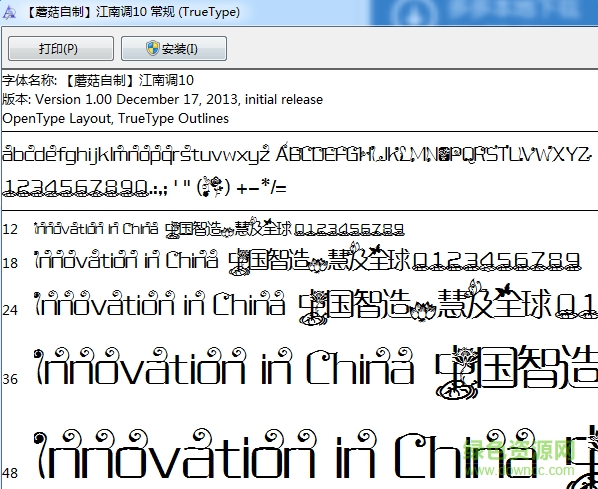
江南調(diào)字體是網(wǎng)友蘑菇自制的一款非常炫酷的個(gè)性字體,你也可以稱(chēng)之為蘑菇自制江南調(diào)10字體。該字體帶有蓮花圖案,線(xiàn)條粗細(xì)適中,字型簡(jiǎn)潔大方得體,整體效果非常出色,并且字庫(kù)完整,可廣泛應(yīng)用于平面設(shè)計(jì)、廣告設(shè)計(jì)、報(bào)紙雜志、正文標(biāo)題等領(lǐng)域,喜歡的網(wǎng)友可免費(fèi)下載收藏。
蘑菇自制江南調(diào)字體具有非常強(qiáng)的藝術(shù)氣息,超多花紋,給字體帶來(lái)生機(jī),有一種別樣的感覺(jué)。歡迎來(lái)綠色資源網(wǎng)下載使用!